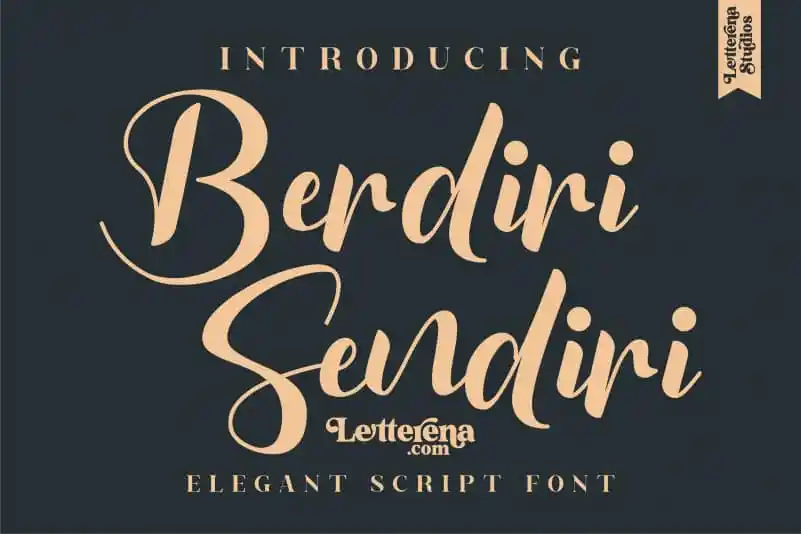
Berdiri Sendiri Script Font – Download Grátis
Berdiri Sendiri Script é uma elegante fonte cíntica criada pela Letterenastudios para projetos que precisam de um toque romântico e sofisticado. Com seu traçado delicadamente fluido, esta fonte cíntica é perfeita para criar ambientes que combinem graça com elegância. Seja você criando um logotipo, desenvolvendo uma marca, projetando móveis de casa, embalagens de produtos, estojos para chá, cartões de lembrança ou capas de livros, a Berdiri Sendiri Script vai fornecer o toque final de sofisticação. Suavemente fluida e com acabamentos cuidadosamente pensados, esta fonte é ideal para qualquer projeto que desejasse um design elegante e autêntico. Estamos certos de que a Berdiri Sendiri Script será uma escolha perfeita para aqueles que buscam personalidade em seus designs, seja para produtos quotidianos ou itens de luxo.